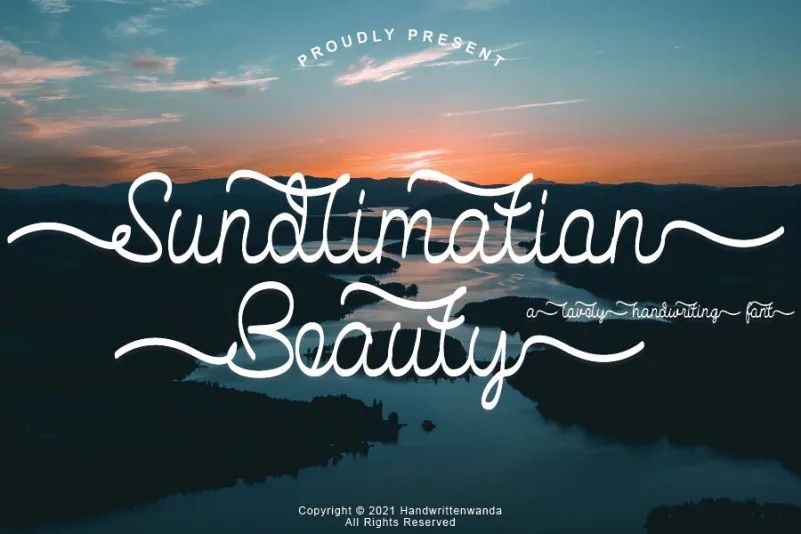
Sundlimation Beauty Font – Download Grátis
A fonte ‘Sundlimation Beauty Font’ é uma elegante caligrafia balanceada e refinada que transmite sofisticação e luxo. Seu estilo alternativo e ligaturas sutis tornam a fonte perfeitamente adequada para qualquer projeto, seja ele de design gráfico, criação de materiais publicitários ou até mesmo para aplicação em letras grandes em uma loja. A elegância do seu traçado é um convite direto para quebrar o estereótipo da fonte tipográfica e transformá-la em algo singular e pessoal, alegando seu uso em cartões de agradecimento ou até mesmo em selos personalizados. Ideal tanto para aquelas pessoas que desejam transmitir elegância através de suas criações quanto para os designers que buscam uma fonte versátil que se adapta perfeitamente às mais diversas necessidades, seja ela em um projeto editorial complexo ou simplesmente estilizando textos com a mão.
Designer: handwrittenwanda